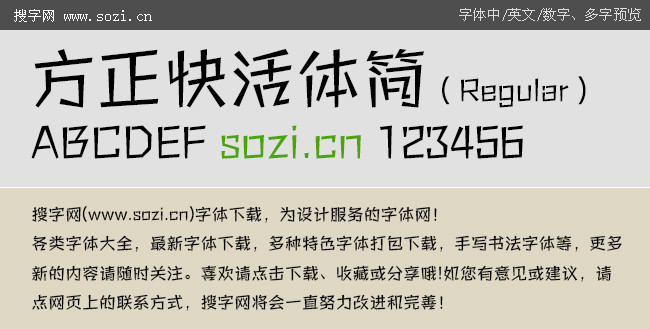
方正快活體簡(jiǎn)Regular
搜字網(wǎng)提供一款方正快活體簡(jiǎn)中文字體下載,方正快活體的創(chuàng)作靈感來源于換牙時(shí)期缺少牙齒的孩童,雖然缺少了牙齒,卻仍然笑容燦爛?旎铙w的“口”形用缺了下劃來表達(dá)特色,形成底部開口(笑容)的布局,充滿趣味性,大膽創(chuàng)新。但又不會(huì)失去字體原來的寫法,一看便知什么字,非常適合兒童,年輕人品牌,飲料,礦泉水和餅店的廣告宣傳和包裝設(shè)計(jì)。